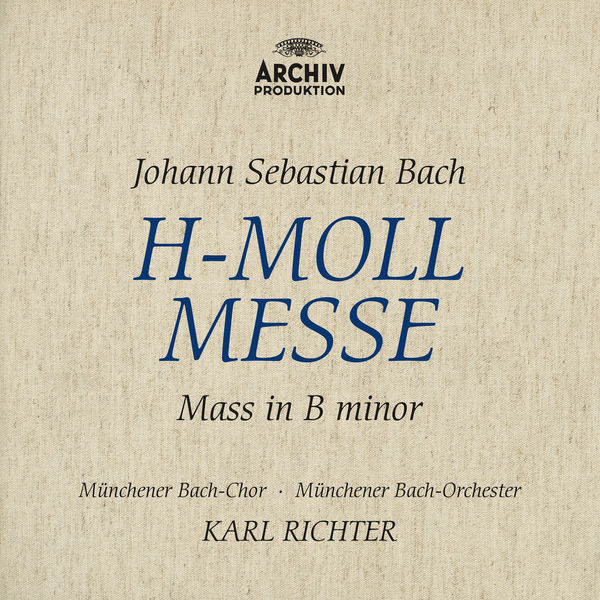
Suche Schriftart von Plattenlabel Archiv Produktion
Ich suche eine bestimme Seriefenschrift, die das Plattenlabel Archiv Produtkion damals verwendet hat. Auffällig ist, dass der Mittelstrich beim E besonder weit oben angesetzt ist und spitzt zuläuft.
Hier ein Beispiel: 600x600bb.jpg
Ich finde die Schrift sehr schön, kann sie aber einfach nicht finden. Mit Palatino war ich bisher am nächsten dran.